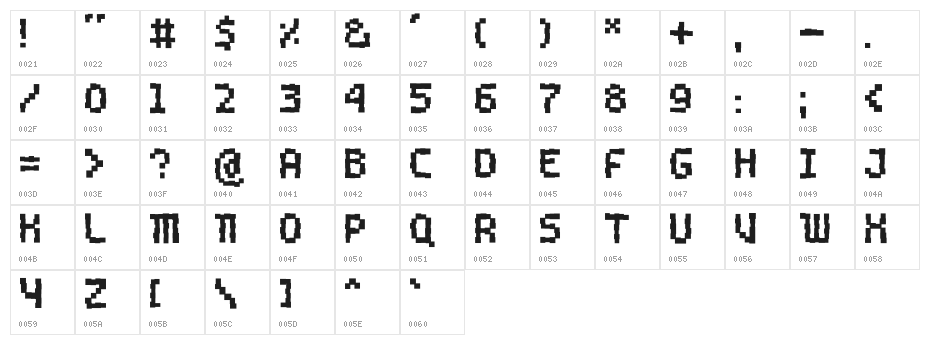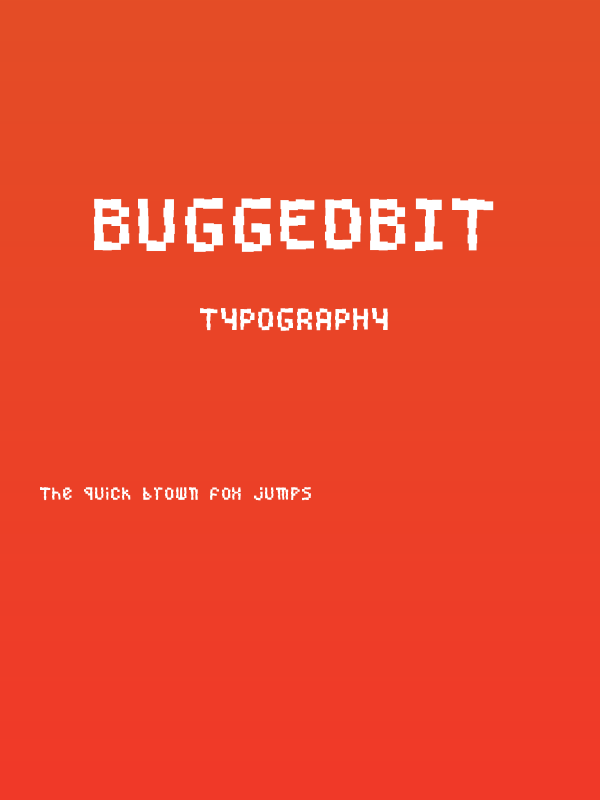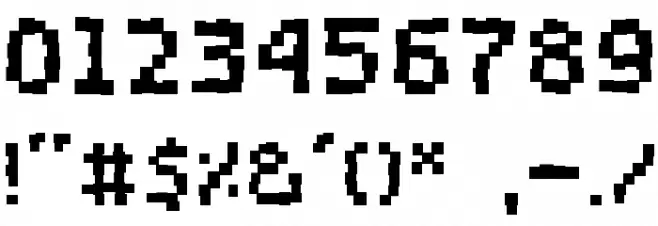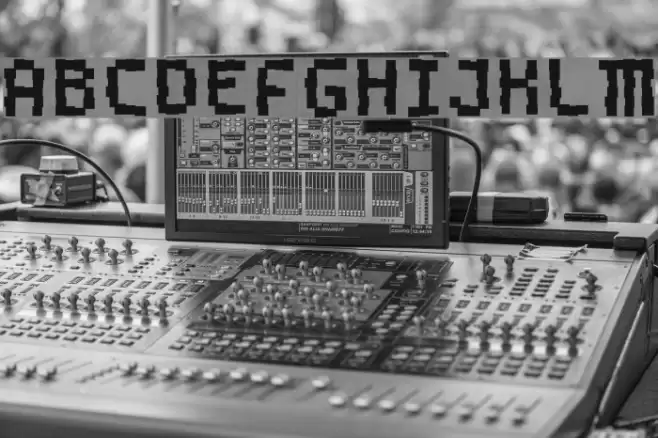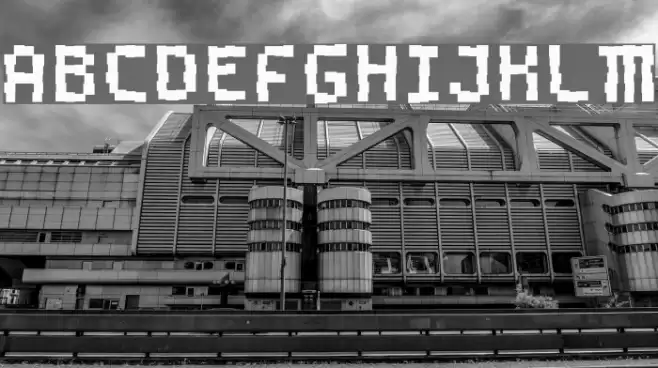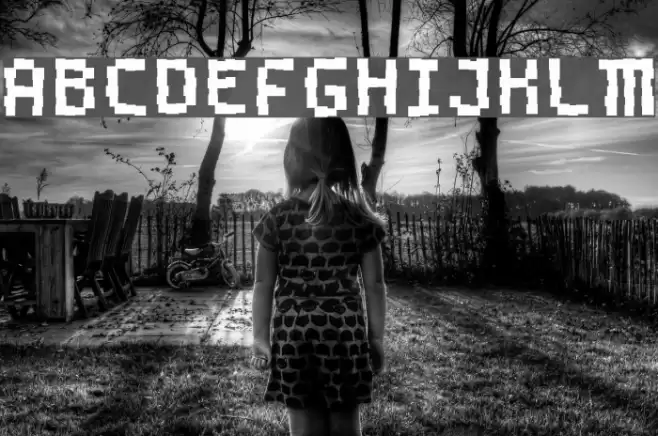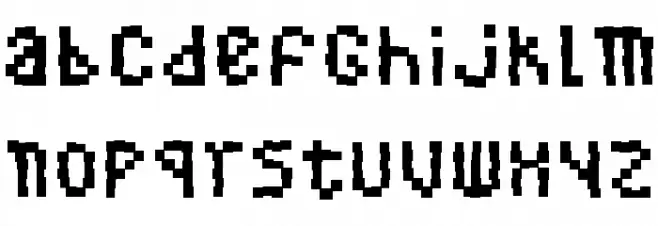
BuggedBit Font
| Gesamtstil | Retro, Digital |
| Anwendungsfall | Headlines, Logos, Digital Art |
| Vorgeschlagene Projekte | Ideal for video game design, tech-themed posters, digital art projects, and retro-style branding. |